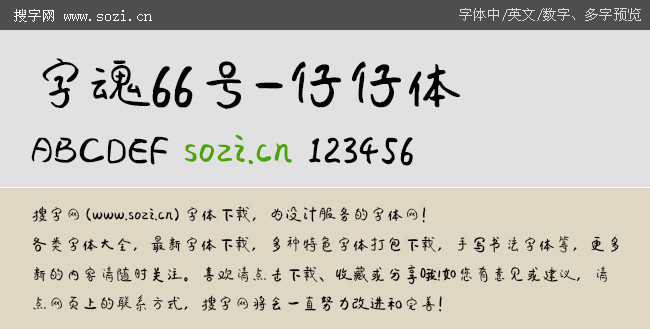
字魂66號-仔仔體
搜字網(wǎng)提供一款字魂66號-仔仔體中文字體下載,該字體是一款卡通可愛手寫字體,該字體包含9280個中文、字母、 符號和數(shù)字,具有動漫、快樂、趣味、中國風 的風格,可以滿足您設計上的各種需求,該字體主要用于圖書、H5、廣告、影視傳媒、青春校園、美食餐飲、活動 等場景。